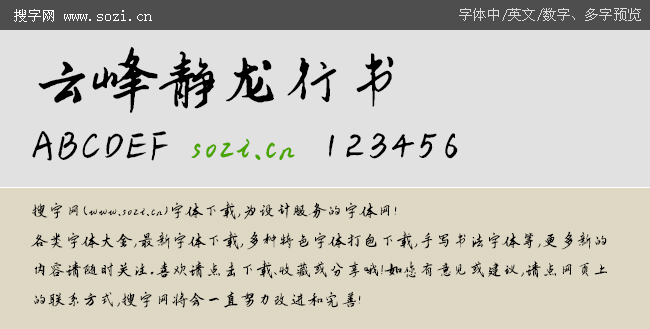
云峰靜龍行書
搜字網(wǎng)給大家提供一款云峰靜龍行書手寫體字體下載,云峰靜龍行書是一款中文手寫風(fēng)格書法字體,字體將比較復(fù)雜的筆畫變的更加簡(jiǎn)單,點(diǎn)畫之間的呼應(yīng)是用勾、挑、牽絲來進(jìn)行加強(qiáng),用圓轉(zhuǎn)的筆畫代替了方折的筆畫。字體特點(diǎn)是端正平穩(wěn),放縱流動(dòng)。適合應(yīng)用于藝術(shù)設(shè)計(jì)、平面宣傳設(shè)計(jì)、標(biāo)題設(shè)計(jì)、海報(bào)設(shè)計(jì)等應(yīng)用。